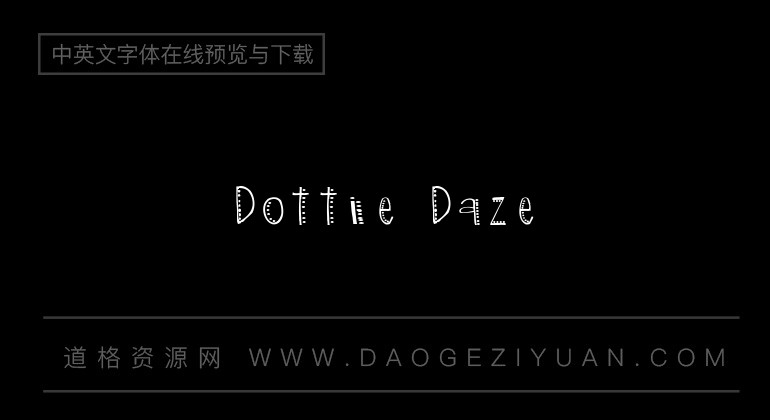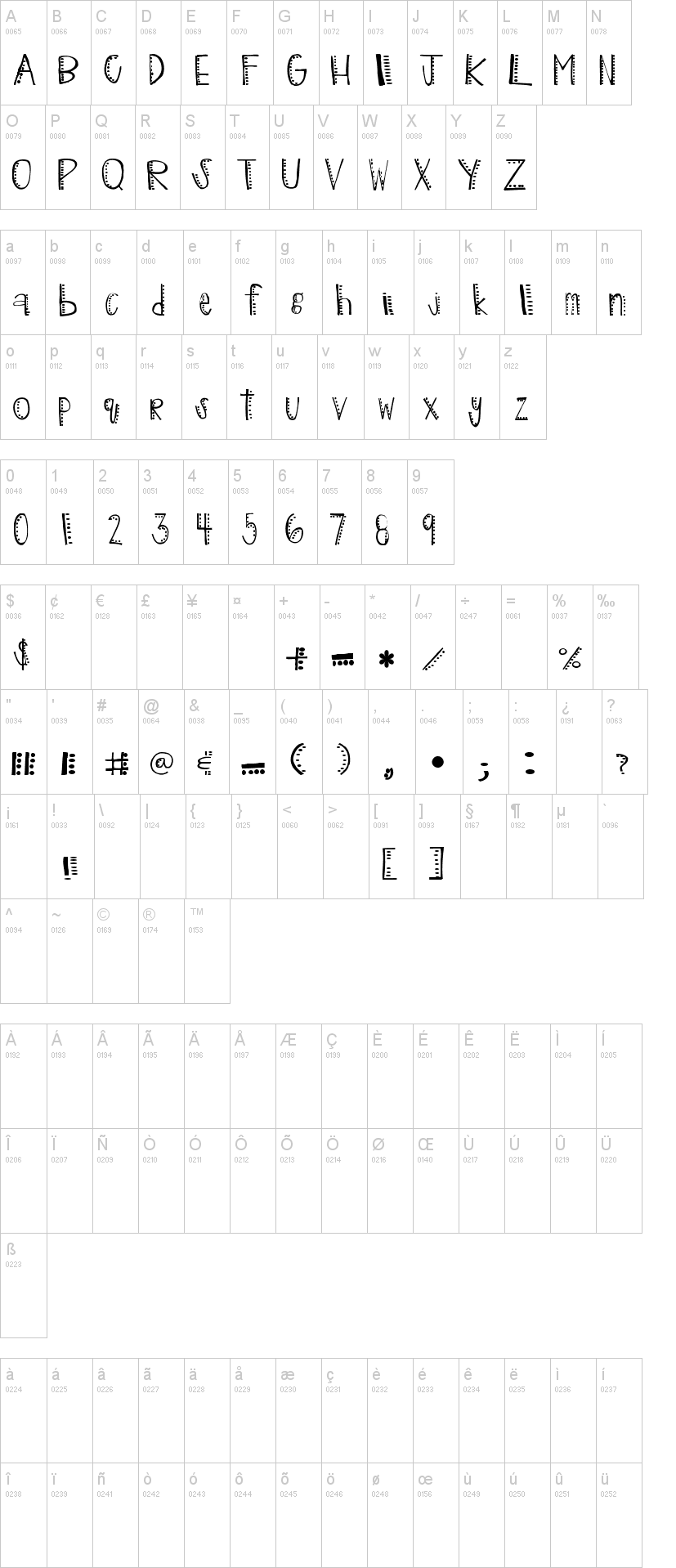
Dottie Daze
Dottie Daze 是一种装饰性的字体,具有手写风格和有趣的外观。它的设计灵感来自于传统的手写日记本和笔迹,同时融入了现代的设计元素。 该字体的特点是每个字符都有一个小点,在字母的交叉点和连接处,这增加了其独特的可读性和视觉吸引力。字体的笔画有一些不规则性,让它看起来更加自然和有机。 Dottie Daze 字体非常适合在设计海报、卡片、标志、标题、广告和其他需要注意力和活力的设计中使用。该字体有多种重量可用,从细到粗的不同版本,让设计师可以选择最适合他们需要的版本。
Dottie Daze是一款非常不错的手写艺术字体,具有很好的视觉感,适合于文化类的宣传设计、商业类品牌的广告和产品包装设计以及个性化文字排版等较多场景。
Dottie Daze字符映射图